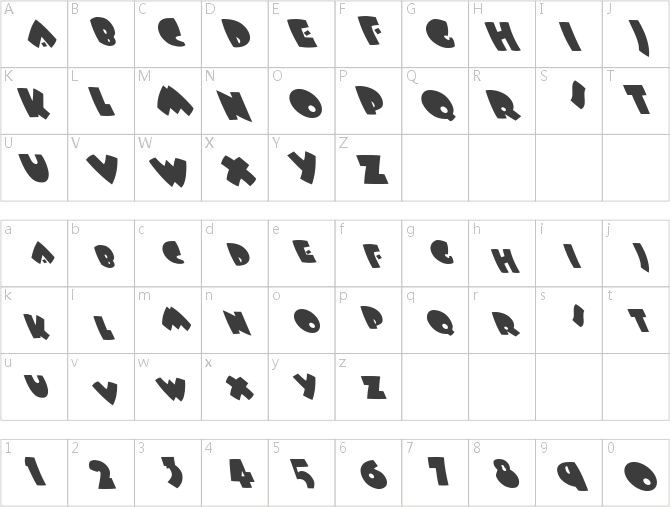
FZ JAZZY 9 LEFTY 詳情頁
字體名稱: FZ JAZZ
FZ JAZZY 9 LEFTY
FZ JAZZY 9 LEFTY介紹
FZ JAZZY 9 LEFTY字體字庫是一款讓人賞心悅目、百看不厭的英文字體,適合各類廣告和產品包裝設計應用,字體大小0.04MB,格式為ttf字體,上傳用戶是志誠設計,作者/版權方為未知